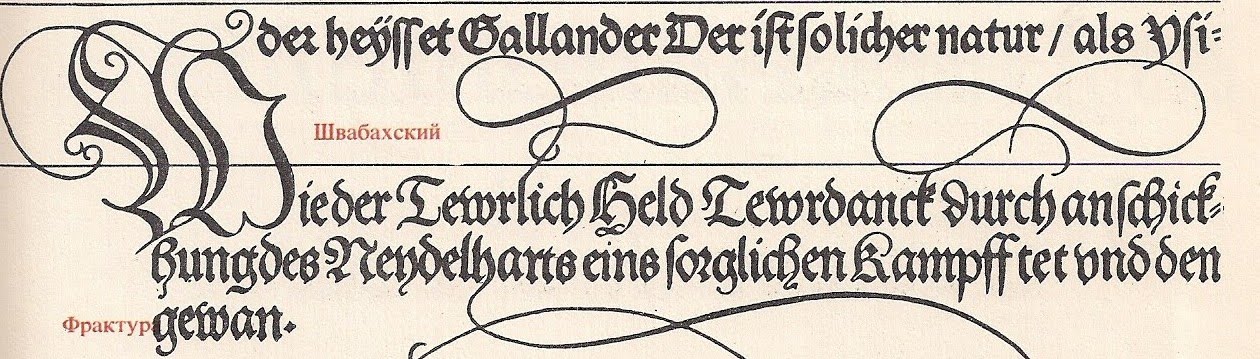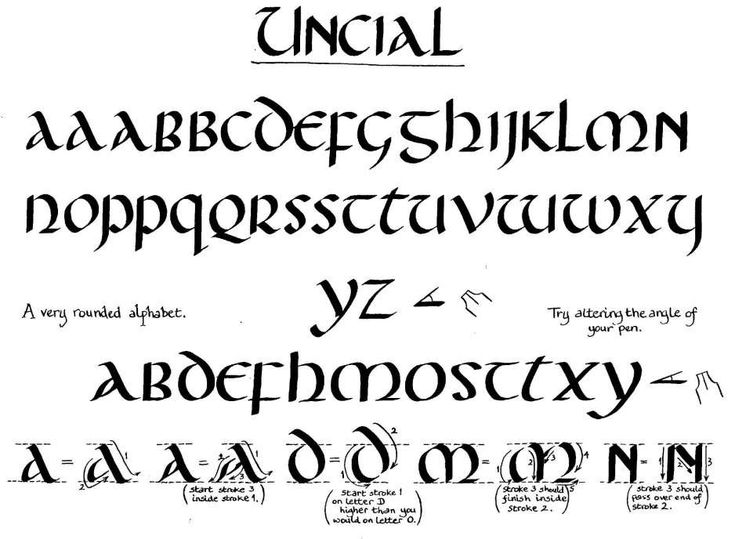
Шрифт и типографика (ШРИФТ) [Реферат №685]
ВВЕДЕНИЕ
Шрифты применяются в самых разнообразных областях науки, техники, архитектуры, дизайна.
Ими пишут буквы, цифры, условные знаки и другие графические символы.
Без шрифтов было бы невозможно создавать книги, плакаты, чертежи, документацию. Каждому виду графической деятельности свойственны определенные шрифты. Авторами являются художники- шрифтовики и художники- графики. Каждый шрифт имеет свой рисунок, свою структуру и конструкцию, которые подчиняются своим эмоциональным законам.
Освоение шрифтов- дело серьезное, поэтому выполнять шрифтовые работы следует внимательно изучив разнообразные конструкции букв и графические приемы. Шрифтовая графика очень многообразна и интересна с исторической точки зрения, так как история шрифта тесно связана с историей письменности.
Глава 1. ШРИФТХудожественные шрифты– это графическая и художественная форма изображения букв и цифр, однородное их начертание, которое придает общий характерный облик. Алфавит– это система расположенных в определенном порядке графических знаков- букв, используемых для закрепления передачи на письме особенностей данного языка. Буква- это графический знак, который сам по себе или в сочетании с другими знаками применяется для обозначения на письме звуков и их разновидностей. Буквы бывают прописные и строчные. Графема– это структура буквы, определяющая ее основной отличительный признак по отношению к дпругим буквам.
Буквы любого шрифта по ширине делится на следующие группы:
Узкие: Б В Г Е Р Ь Ъ
Нормальные: А Д З И К Л Н П Т У Х Ц Ч Я
Широкие: Ж М О С Ф Ш Щ Ы Э Ю
Кроме того, буквы делятся на прямоугольные ( Н П Л ), круглые ( О Э С) и комбинированные ( Б Р Ю ).
Исторические виды письма:
Пиктографическое- первобытное письмо в виде наскальных повествовательных рисунков.
Идеографическое- выполняется при помощи идеограмм, а не букв, когда одним знаком обозначается целое понятие или слово.
Слоговое– один знак обозначает слог.
Буквенно- звуковое– знаки обозначают отдельные звуки.
Готический Славянский– один из видов славянской вязи.
Греческий и Римский- рубленный: одинаковая толщина штриховки, нет засечек, брусковый: одинаковая толщина штрихов и прямоугольные засечки, антиква: разная толщина штрихов, заостренные с краю засечки, скругление в месте присоединения к основному штриху.
Свободный: декоративный, художественный, каллиграфический.
Курсивный шрифт– шрифт, имеющий наклон 75 градусов. Курсивные шрифты очень разнообразны и имеют большие возможности для составления авторских разновидностей шрифта. Красота заложена в самой конструкции буквы, в умении найти гармоничное сочетание размеров для составления авторских разновидностей шрифта.
Русская титульная вязь– одинаковые расстояния между главными элементами букв и расстояние между ними.
Готические инициалы– в основу написания готического письма положен принцип работы ширококонечным пером с дополнительной доработкой остроконечным пером.
Элементы шрифта:
- Основной штрих
- Соединительный штрих
- Засечка
- Засечка вертикальная
- Внутрибуквенный просвет
- Верхний выносной элемент
- Нижний выносной элемент
- Наплыв
- Межбуквенный просвет
- Высота прописных букв
- Линия округлых и остроконечных букв
- Междустрочный пробел
- Высота строчных букв
(См.
Рис. 1)
Рис. 1. Элементы шрифта
К основным штрихам относятся вертикальные штрихи и косые, направленные сверху вниз (считая слева направо). В большинстве гарнитур (но не во всех) эти штрихи толще остальных.
Соединительные штрихи — это горизонтальные штрихи и косые, направленные снизу вверх. В большинстве гарнитур они тоньше основных.
Основные и соединительные штрихи типографского шрифта соответствуют нажимным и безнажимным штрихам рукописного шрифта (почерка). Это естественно, ведь печатной книге предшествовала рукописная, и лучшие почерки ее переписчиков служили прототипом для типографских шрифтов.
В буквах, образованных от круга или овала, основным штрихам соответствуют наплывы — утолщения, расположенные посередине высоты букв или несколько смещенные вниз (в левой половине буквы) и вверх (в правой ее половине). И эта особенность напоминает о связи типографских шрифтов с рукописными.
К важнейшим концевым элементам букв относятся: засечки — небольшие штрихи, подчеркивающие основные и некоторые дополнительные штрихи; точки и «хвостики», которыми заканчиваются некоторые штрихи.